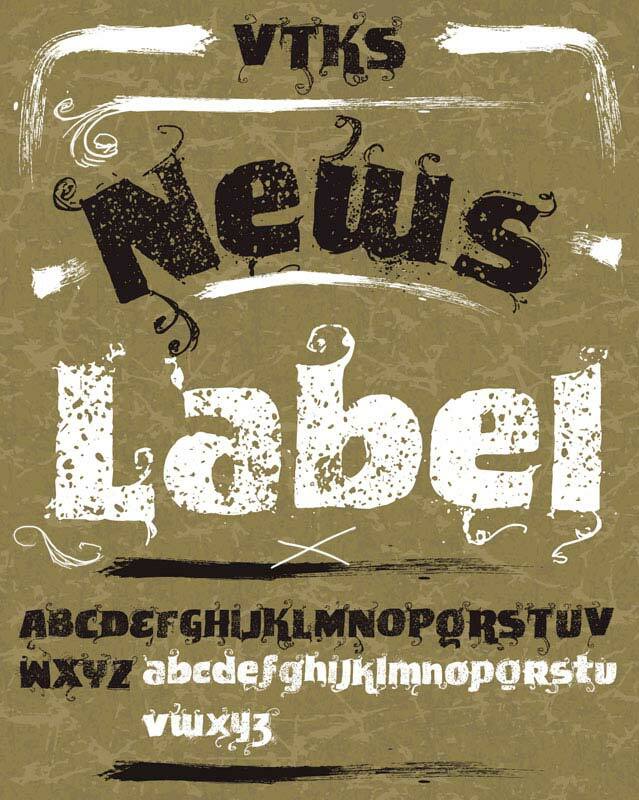
VTKS News Label di Douglas Vitkauskas è un font display gratuito, caratterizzato da curve e un mood ruvido che ricorda la vecchia carta di giornale. Le lettere appaiono massicce e pesanti a un primo sguardo, per poi sciogliersi in riccioli sottili e svolazzi, mentre la texture consumata conferisce a tutto il design un aspetto inchiostrato, vissuto e leggermente ribelle.
Questo mix è perfetto per titoli di poster, copertine di fanzine, volantini, insegne e cartelli dove un font gratuito può permettersi un po' di grana senza risultare troppo levigato. Funziona bene anche per branding breve, capilettera e nomi in stile etichetta, perché quelle estremità ricciolute donano un tocco artigianale e curato, anche su poche lettere.